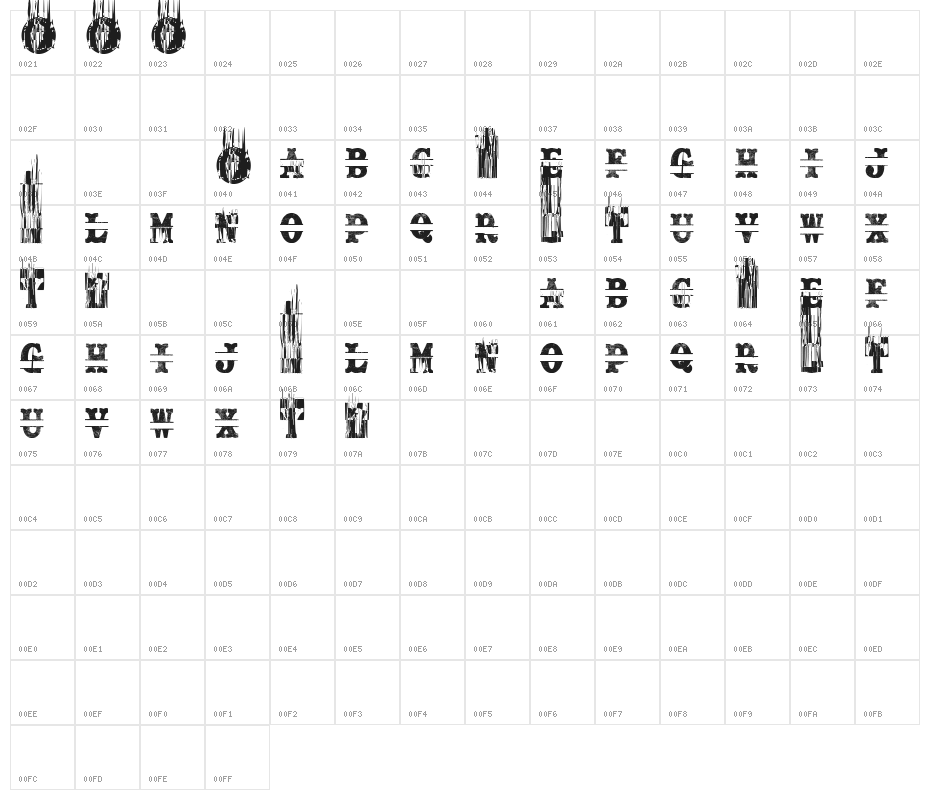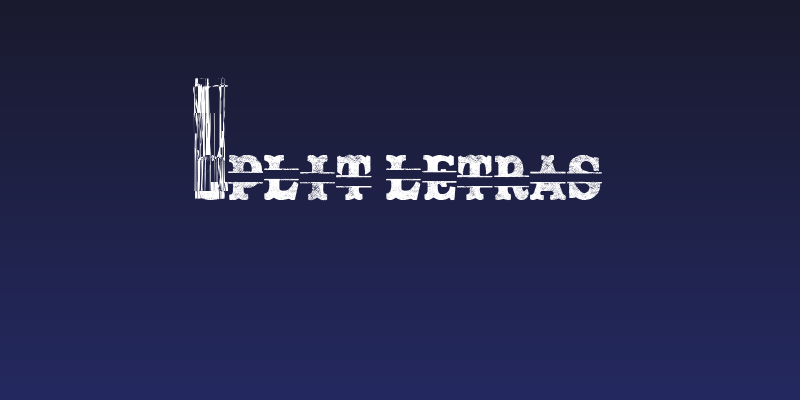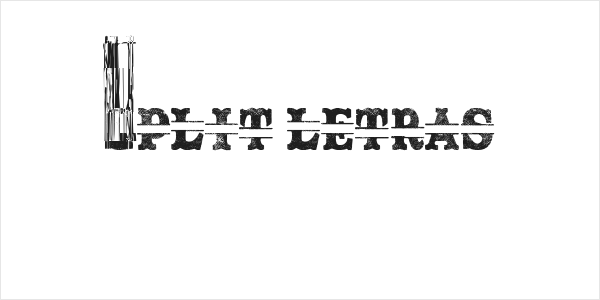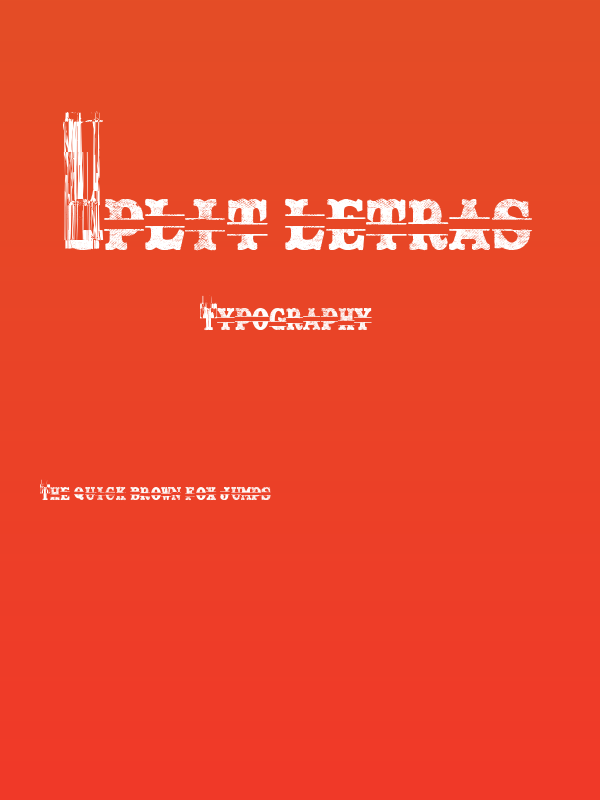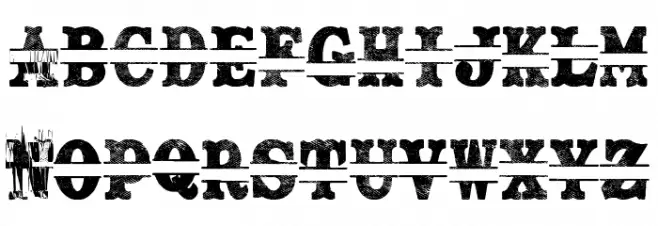
Split Letras Font
✎ Retro
| الفئات | Retro |
| النمط العام | Vintage, Industrial |
| مشاريع مقترحة | Ideal for poster designs, album covers, branding projects, and any creative work that requires a bold, vintage-inspired aesthetic. |